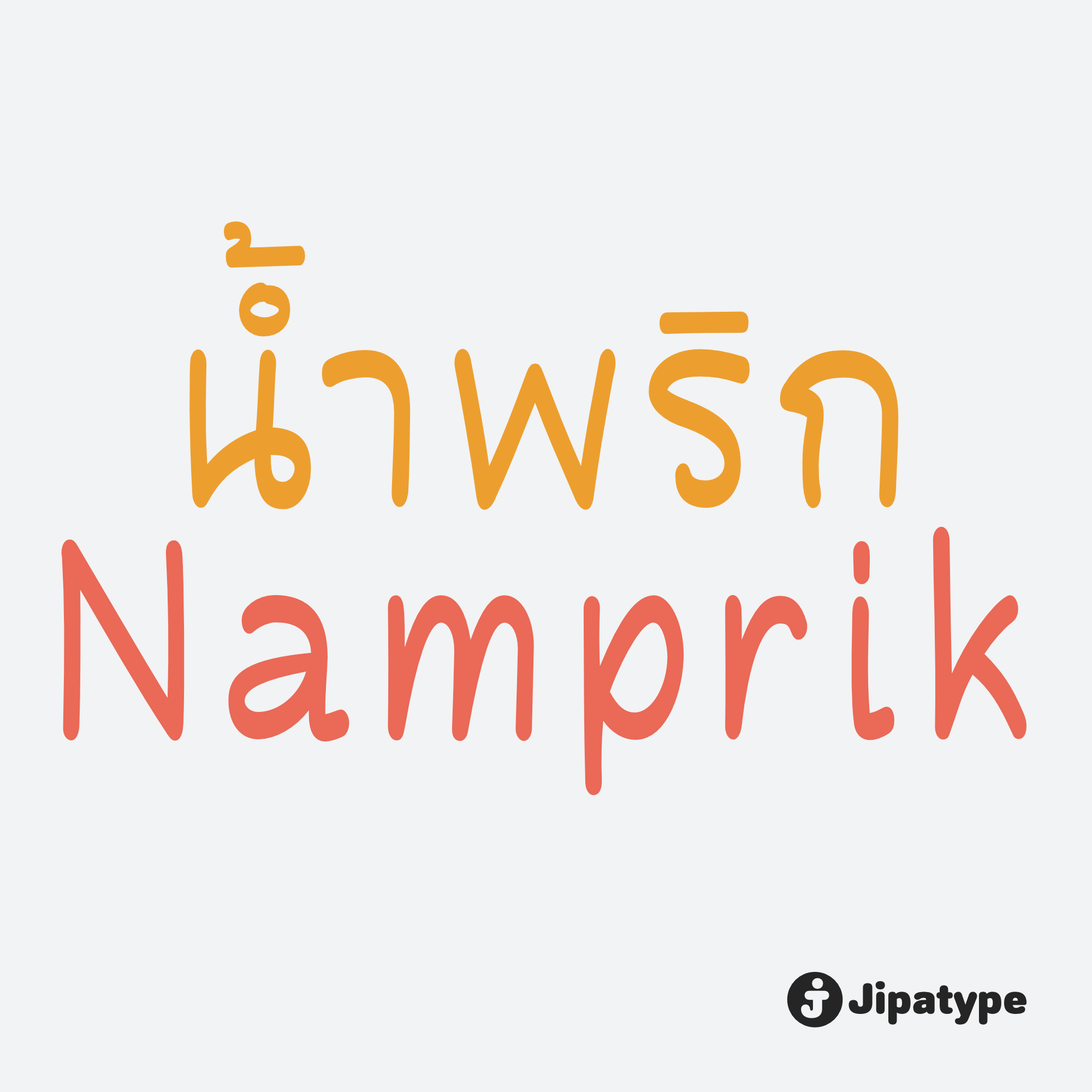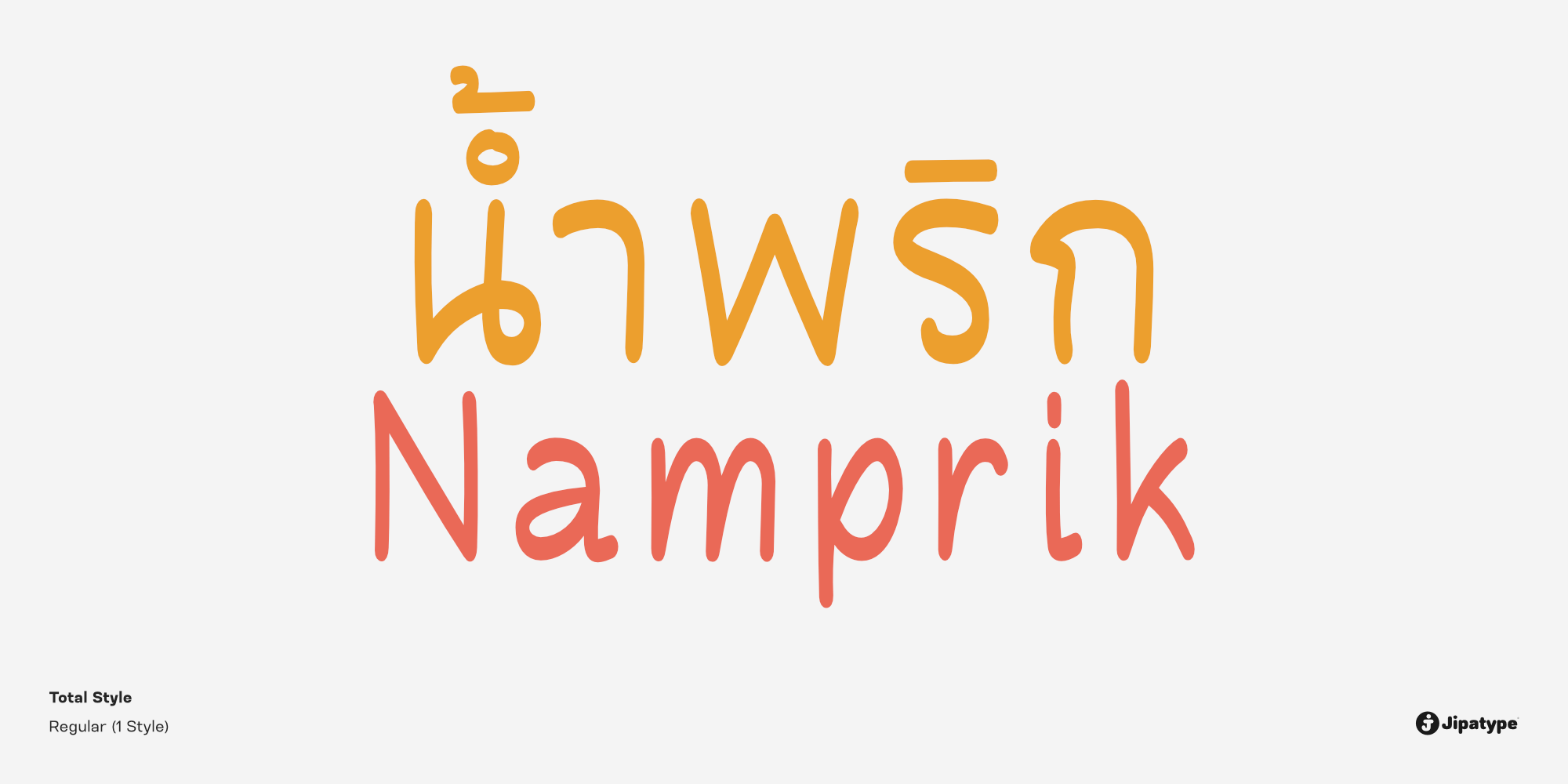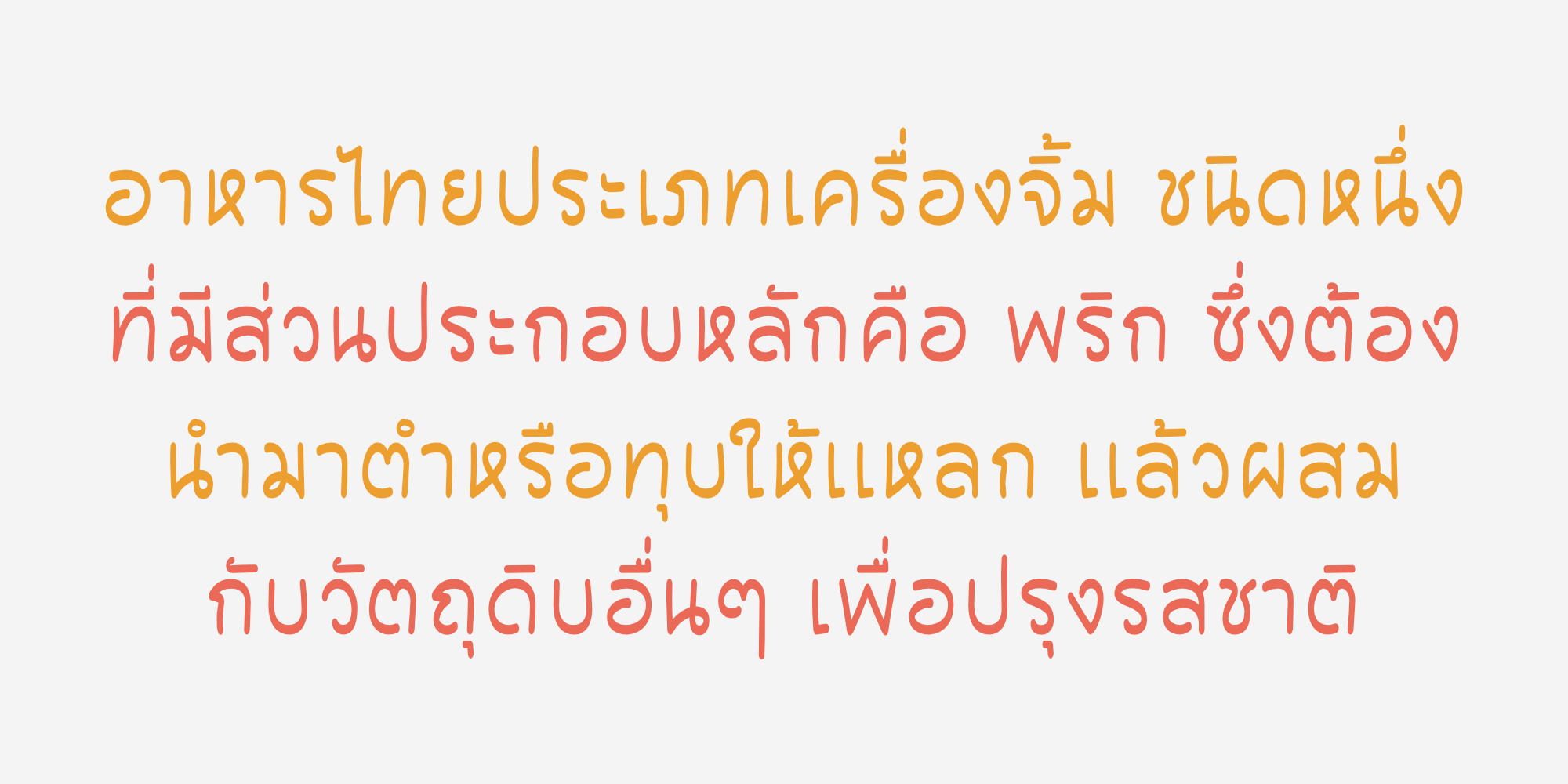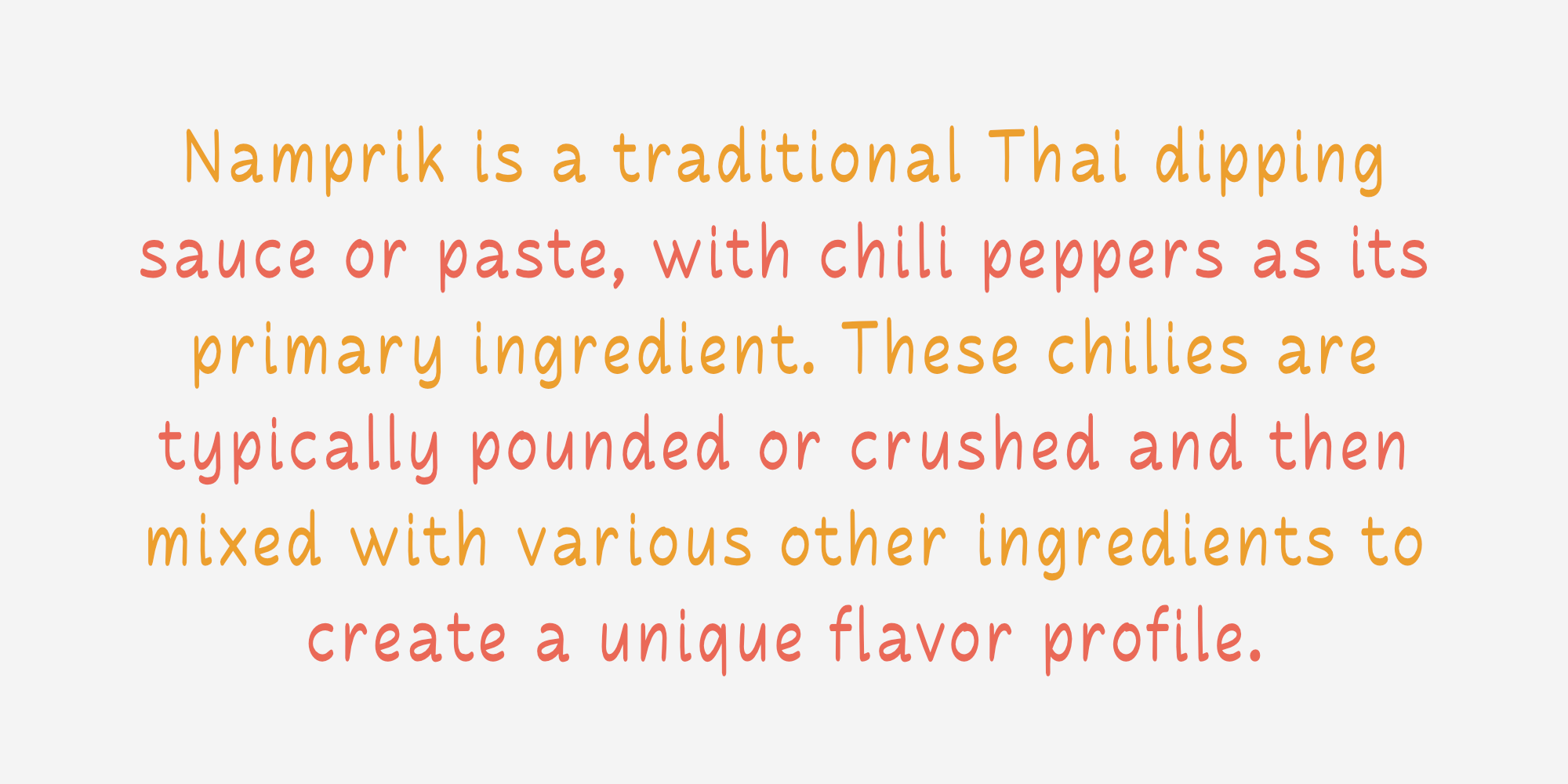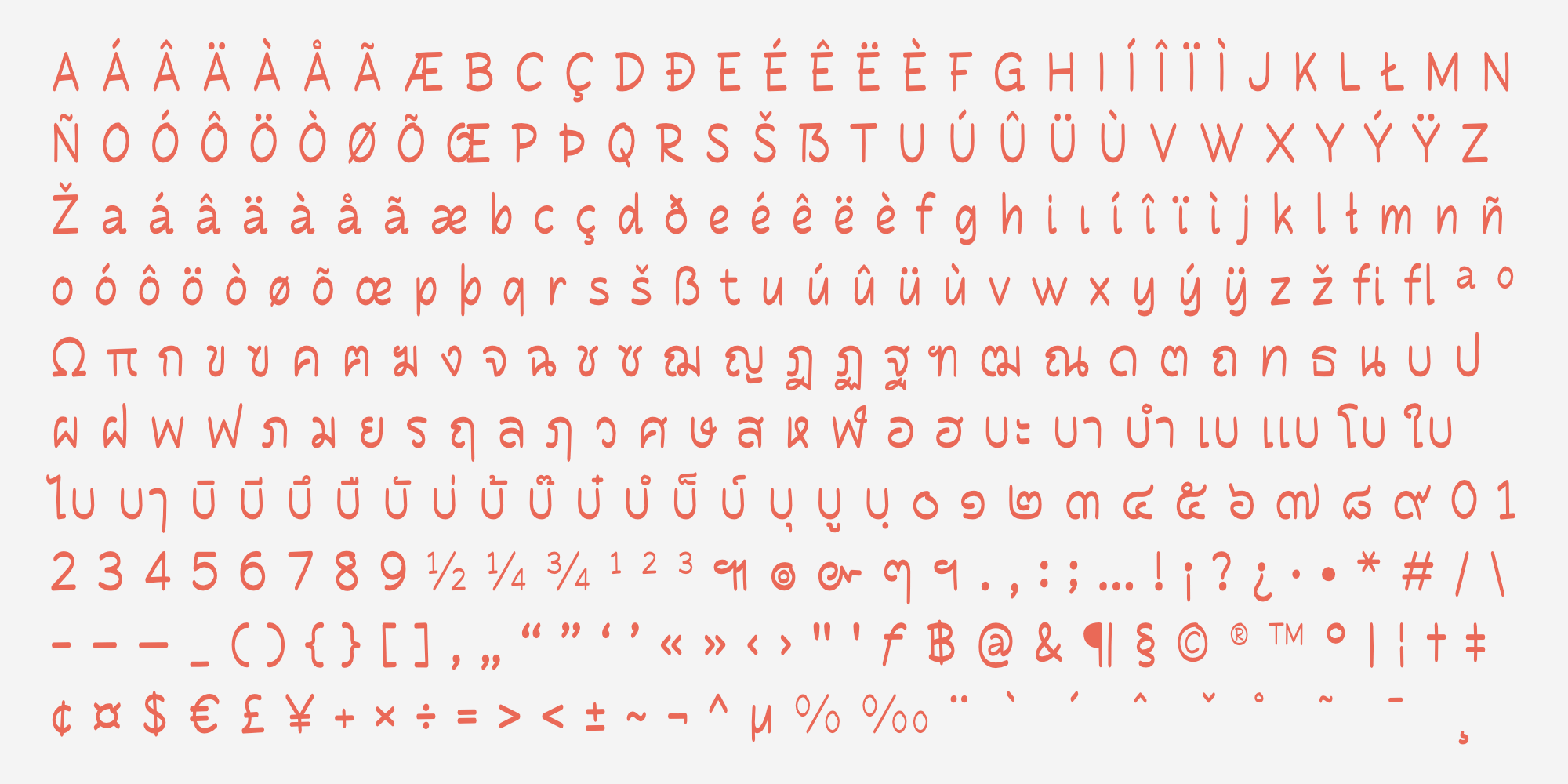
Namprik คือแบบอักษรสไตล์ลายมือที่โดดเด่นด้วยบุคลิกที่อบอุ่น เป็นกันเอง และดูขี้เล่นอย่างเป็นธรรมชาติ ตัวอักษรมีลักษณะเส้นโค้งมน ปลายเส้นมีความนุ่มนวลเสมือนเขียนด้วยปากกาเมจิก ให้ความรู้สึกที่ลื่นไหล ผ่อนคลาย และไม่เป็นทางการจนเกินไป แต่ยังคงไว้ซึ่งความอ่านง่ายสะอาดตา
เหมาะอย่างยิ่งสำหรับการนำไปใช้ในงานออกแบบที่ต้องการสื่อถึงความใส่ใจ ความเป็นโฮมเมด หรือความสดใสสนุกสนาน เช่น การออกแบบบรรจุภัณฑ์อาหารและขนม เมนูร้านคาเฟ่สไตล์มินิมอล สื่อการเรียนรู้สำหรับเด็ก หรืองานกราฟิกบนโซเชียลมีเดียที่ต้องการสร้างปฏิสัมพันธ์ที่เป็นมิตรและเข้าถึงผู้คนได้ง่าย